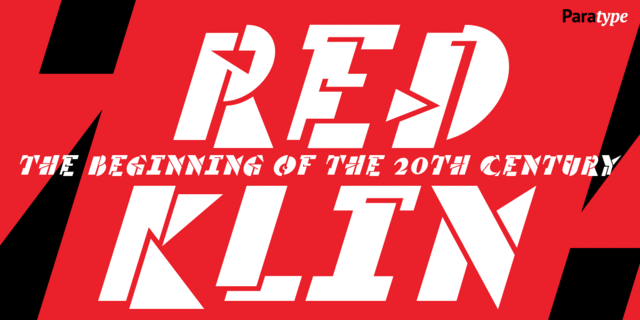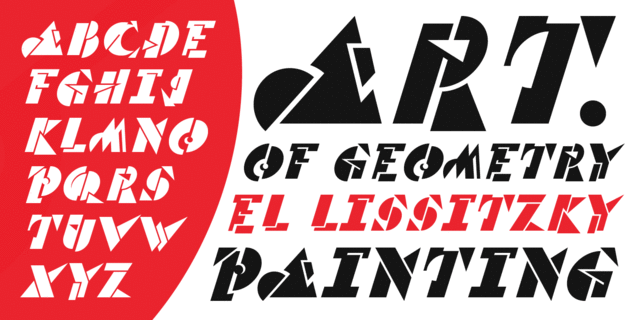
Red Klin (1 шрифт)
Декоративный шрифт, разработанный для фирмы ПараТайп в 2004 году дизайнером Гаянэ Багдасарян. Создан по мотивам русского изобразительного искусства начала ХХ века - рисованных шрифтов Сергея Чехонина (1878-1936), графического дизайна Эль Лисицкого (1890-1941) и супрематической живописи. Шрифт состоит только из прописных знаков. Первоначальная эскизная версия шрифта под именем Клин была награждена дипломом TDC2 2000. Шрифт предназначен для использования в буквицах, заголовках, рекламе.
гострий, різкий, чіткий, комуністичний, червоний, революційний, монументальний, динамічний, артистичний, виразний, яскравий, помітний, гучний, робочий, кричущий